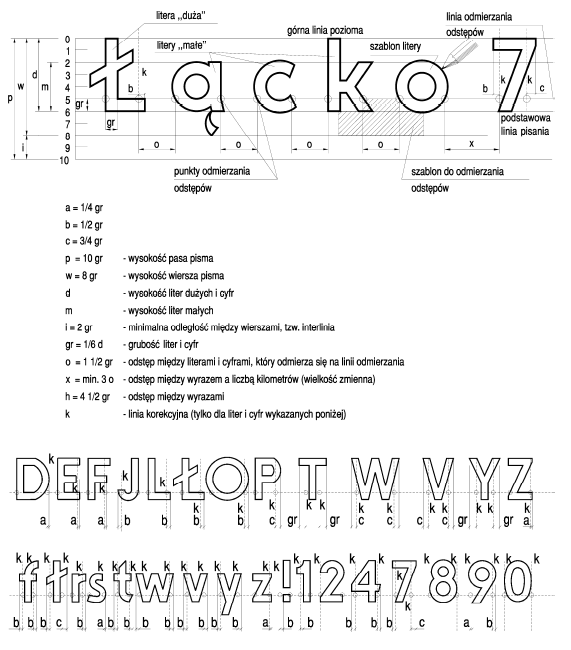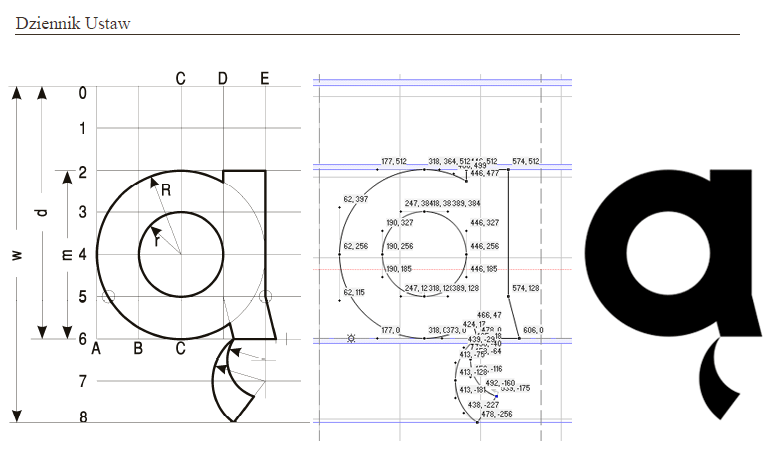
Ponieważ przez długi czas nie było dostępnego fontu z liternictwem z tablic drogowych, przygotowaliśmy profesjonalny font zgodny z wytycznymi Dziennika Ustaw.
Litery zostały starannie zaprojektowane uwzględniając zalecenia projektanta.
(Źródło: DZIENNIK USTAW RZECZYPOSPOLITEJ POLSKIEJ
z dnia 26 listopada 2019 r. Poz. 2311)   |